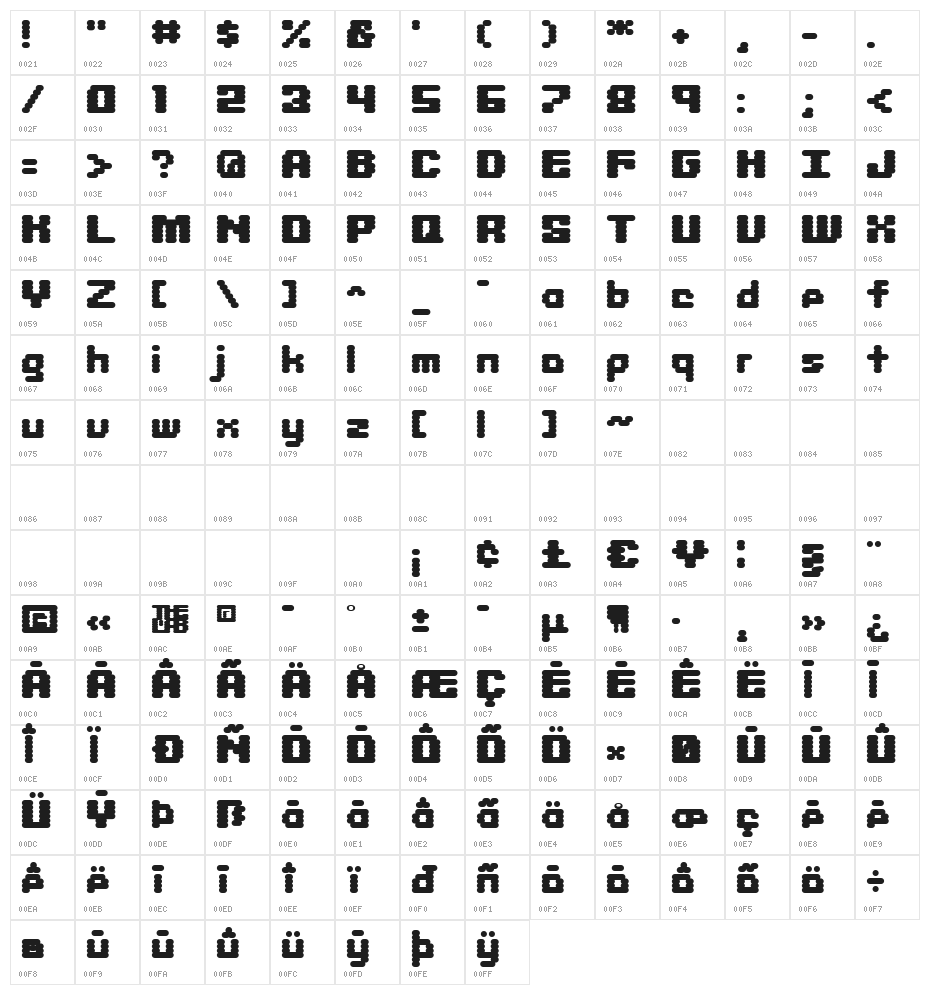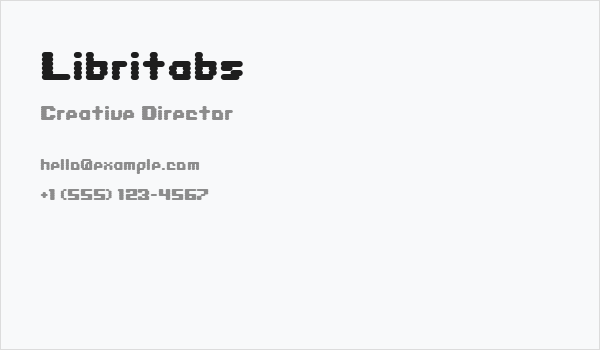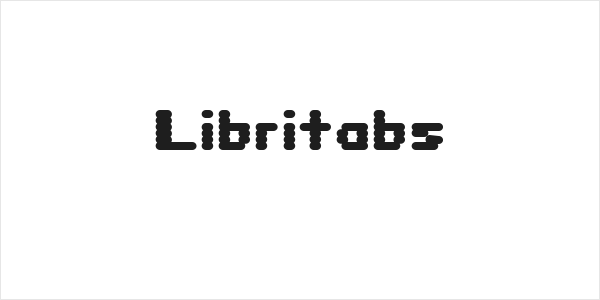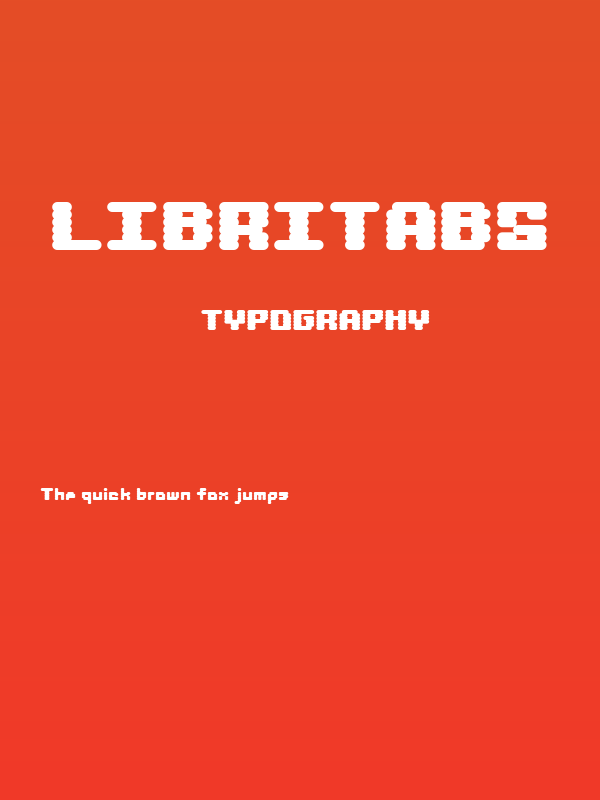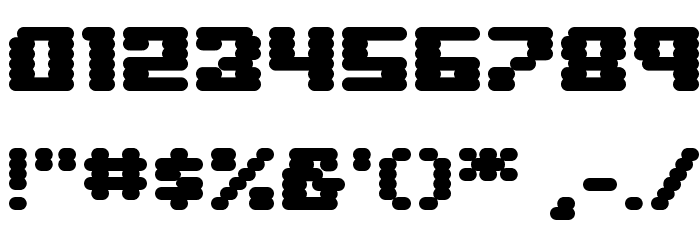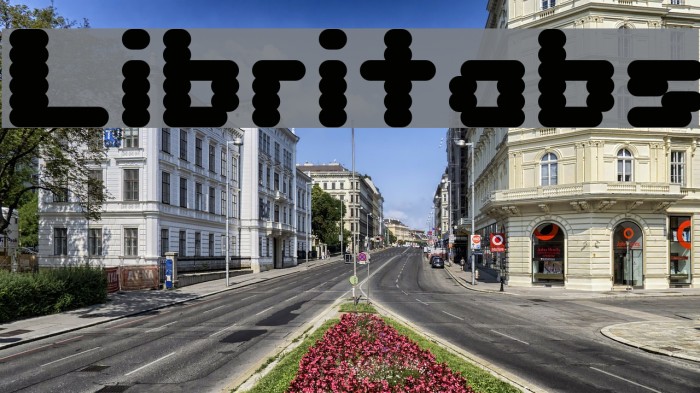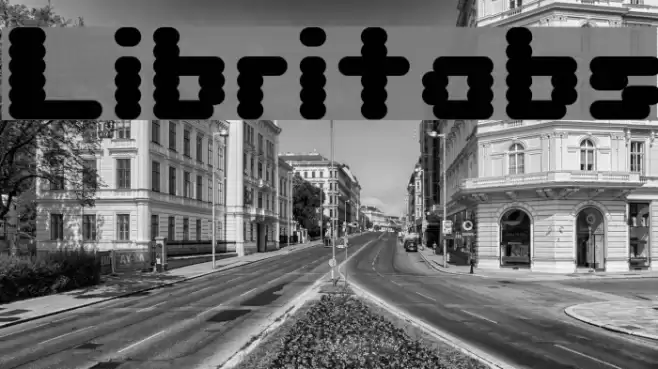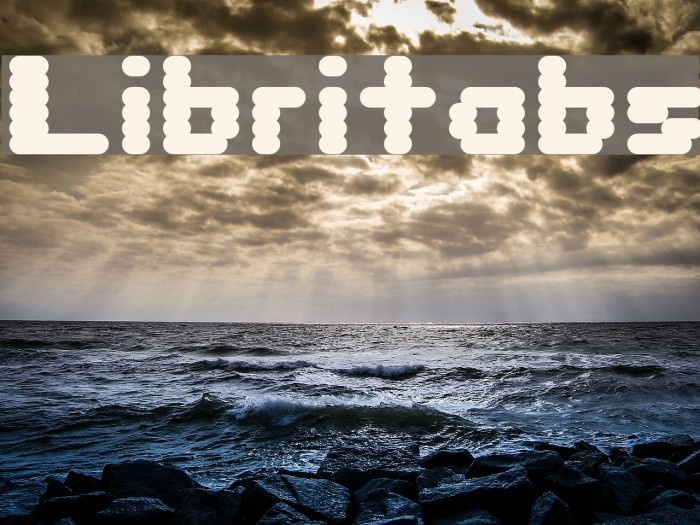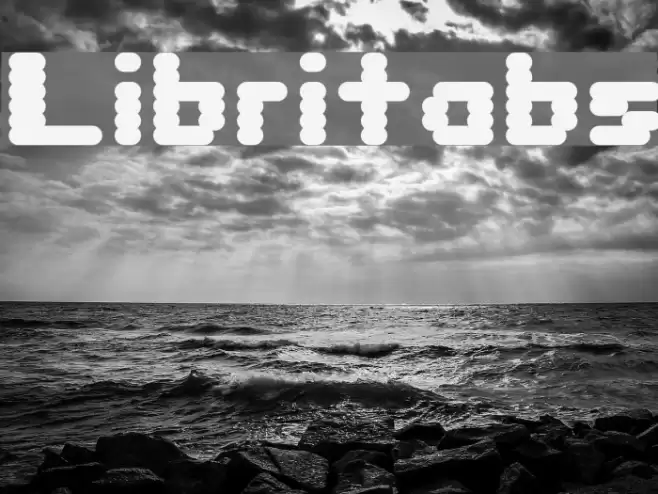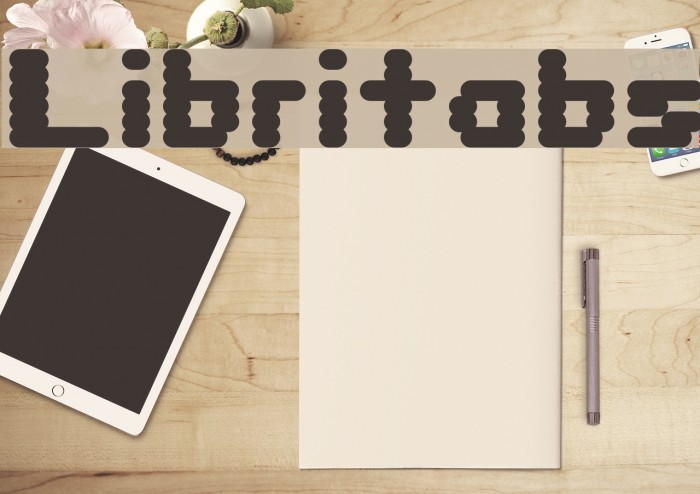
Libritabs Font
| Gesamtstil | Playful, Modern |
| Vorgeschlagene Projekte | Ideal for children's books, playful branding, party invitations, and creative posters. |